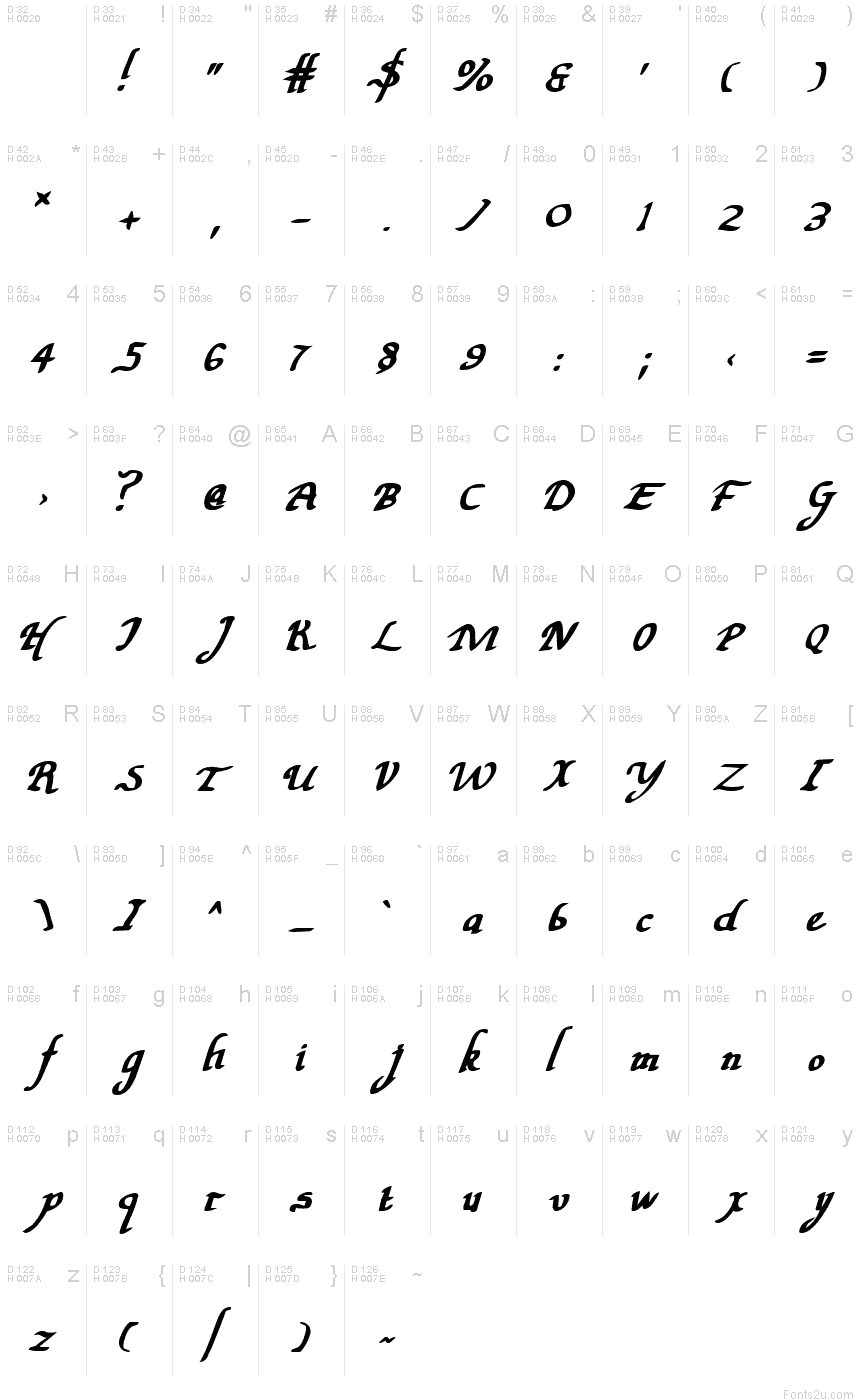
Valley Forge Bold Italic od Iconian Fonts to darmowy krój brush-script o szybkim, pochyłym rytmie i ostro zakończonych pociągnięciach. Litery łączą szerokie, atramentowe smugi z wąskimi łączeniami, co nadaje napisom energiczny, odręczny charakter.
Dramatyczny kontrast wprowadza dynamikę na plakatach muzycznych i identyfikacji festiwali, a długie krzywe wnoszą klimat vintage’owych szyldów na opakowania napojów. Wybierz ten darmowy font do oprawy albumów, nagłówków redakcyjnych lub grafik do mediów społecznościowych, gdy typografia ma sprawiać wrażenie spontanicznej, nie tracąc przy tym wyraźnego kształtu.